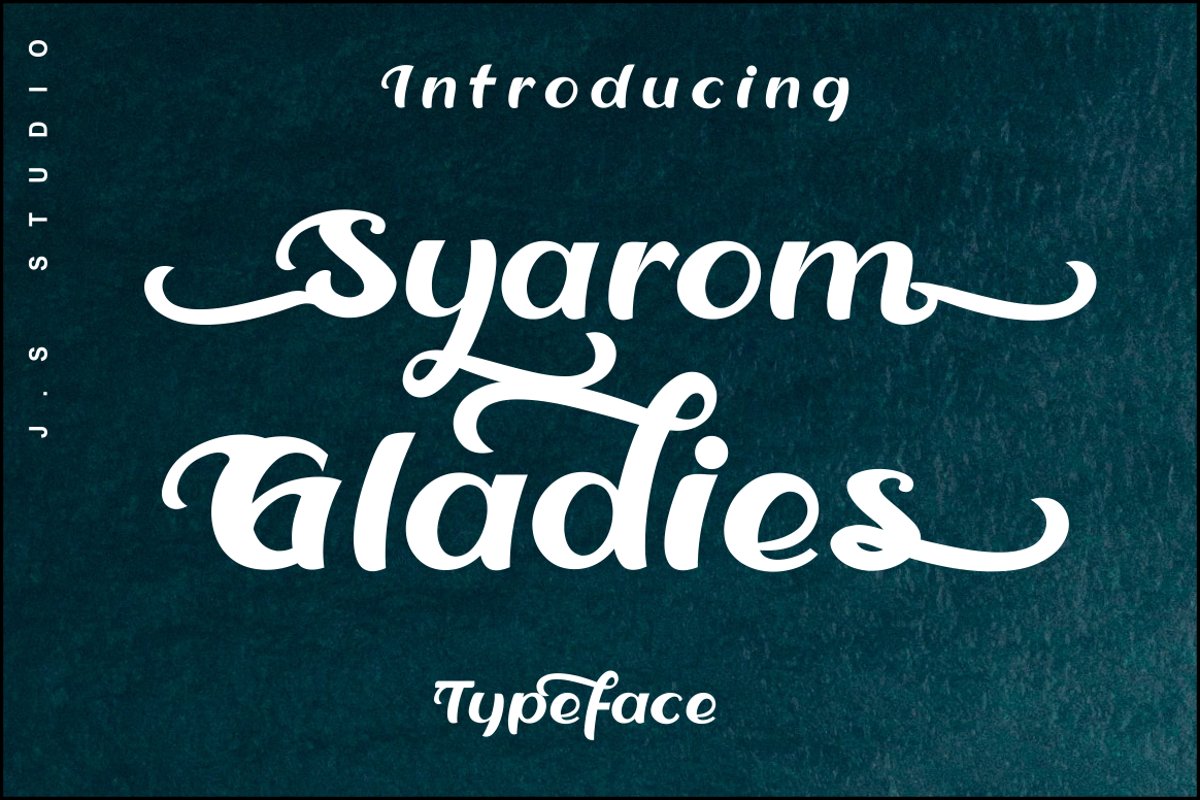
syarom gladies
syarom gladias adalah font tulisan tangan yang indah dan memiliki set alternatif.
sangat cocok untuk logo, sampul album. pernikahan.
fotografi.
Anda dapat menggunakan font ini dengan berbagai karakter font.